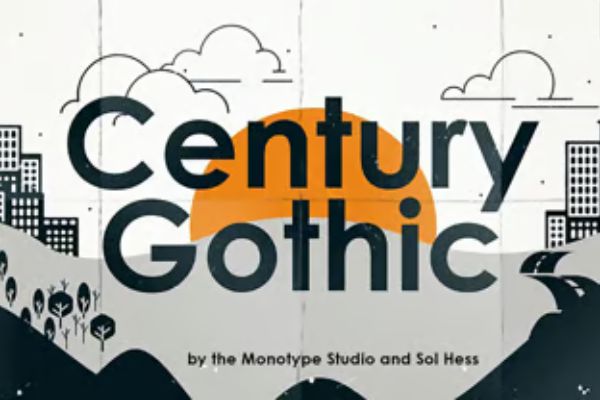
Century Gothic™ Pro Bold Italic
Century Gothic 字体风格开放、友好,适用于标题展示以及少量文本。Century Gothic 广泛应用于广告和媒体标题,包括电视节目和电影标识。清晰干净的设计使其也经常出现在语言教学中。在更国际化的交流应用中,W1G 版本具有泛欧字符集,包含拉丁文、希腊文和西里尔文,因此支持西欧、东欧和中欧官方使用的所有语言和书写系统。